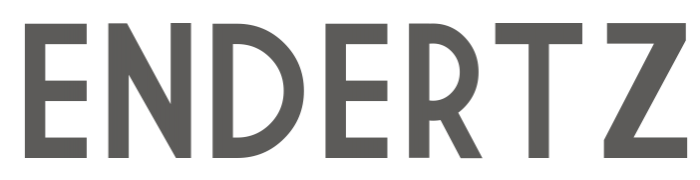
schriftart für ein konstruktionsbüro
ich hätte diese schrift gern etwas dünner. die vorhandene schriftart "market deco" gibt das aber nicht her. könnt ihr mir bitte sagen, welche schriftart in frage kommen könnte?
Brauchst Du nur den Schriftzug ENDERTZ etwas leichter (das wäre in fünf Minuten gebastelt) oder brauchst Du die ganze Schrift in einem leichteren Schnitt?